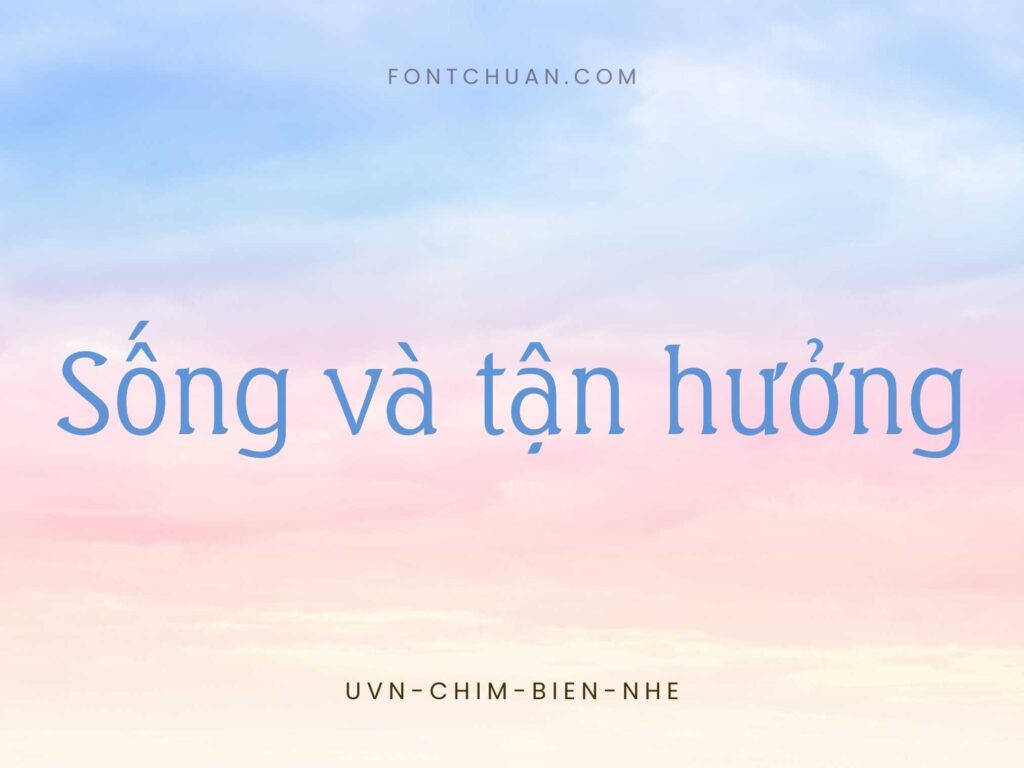
Font UVN Chim Bien Nhe Việt Hóa
UVN Chim Biển Nhẹ là một phông chữ serif được thiết kế bởi Tom Trương vào năm 2001. Phông chữ này mang phong cách cổ điển với các đường nét thanh mảnh và tinh tế, tạo nên sự trang nhã và dễ đọc trong thiết kế. UVN Chim Biển Nhẹ hỗ trợ đầy đủ các ký tự tiếng Việt, giúp người dùng tại Việt Nam dễ dàng sử dụng trong các dự án sáng tạo của mình.
Với thiết kế thanh lịch và rõ ràng, UVN Chim Biển Nhẹ phù hợp cho các ứng dụng như văn bản dài, sách, tạp chí, thiết kế logo và các ấn phẩm cần sự nhấn mạnh. Trong lĩnh vực sự kiện, phông chữ này có thể được sử dụng trong các dịp như hội thảo, triển lãm và các sự kiện văn hóa. Ngoài ra, UVN Chim Biển Nhẹ cũng thích hợp cho các ngành nghề như thiết kế đồ họa, in ấn và xuất bản.